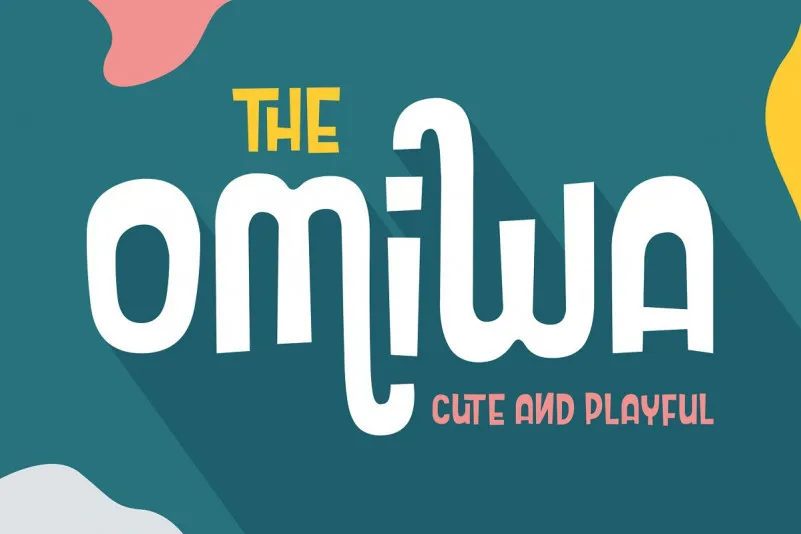
A fonte Omiwa Typeface é uma opção irresistível para aqueles que desejam dar um toque amigável a seus projetos design. Esta fonte Script é ideal tanto para aplicativos profissionais quanto para tarefas criativas, seja no desenvolvimento de logotipos ou em postagens de blog. A Omiwa apresenta uma combinação única de simplicidade e versatilidade que tornam-a perfeita para diversas propostas de projeto gráfico. Com seu estilo único e linhas monolineares, a fonte Omiwa oferece uma experiência visual envolvente que pode ser facilmente adaptada para criar efeitos impactantes. Seja com nomes ou frases, ela é perfeita para projetos que exigem um enfoque de design versátil e elegante. Para designers inquietos e criativos, a Omiwa oferece uma fonte ideal para qualquer projeto imaginável, seja um logotipo vibrante, um quote impactante ou até mesmo uma identidade visual completa. Com alternativas únicas na sua composição, é fácil criar padrões memoráveis que se destacam em seu trabalho de design. Seja qual for a aplicação da fonte Omiwa Typeface, ela certamente se destaca como um recurso de recursos gráficos indispensável para qualquer designer que deseja manter seu projeto profissionalmente moderno e cheio de personalidade.